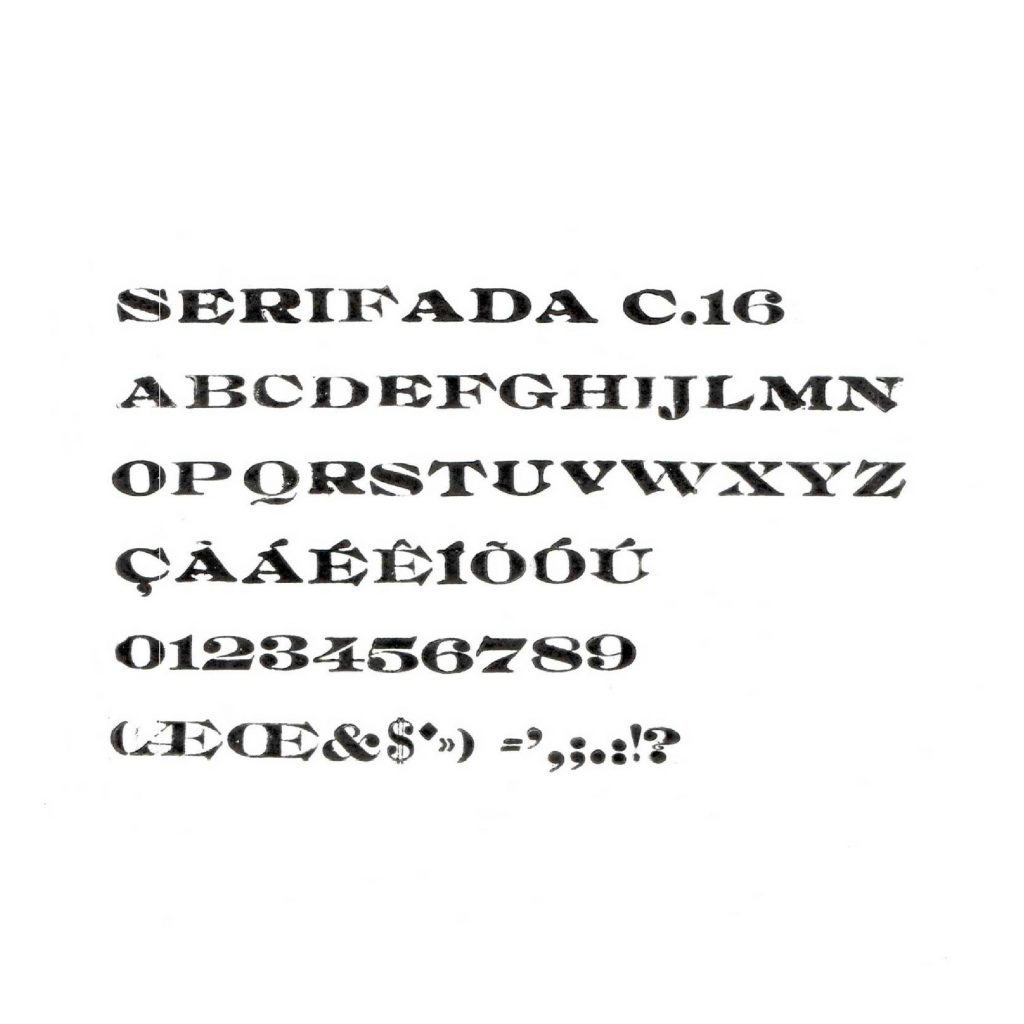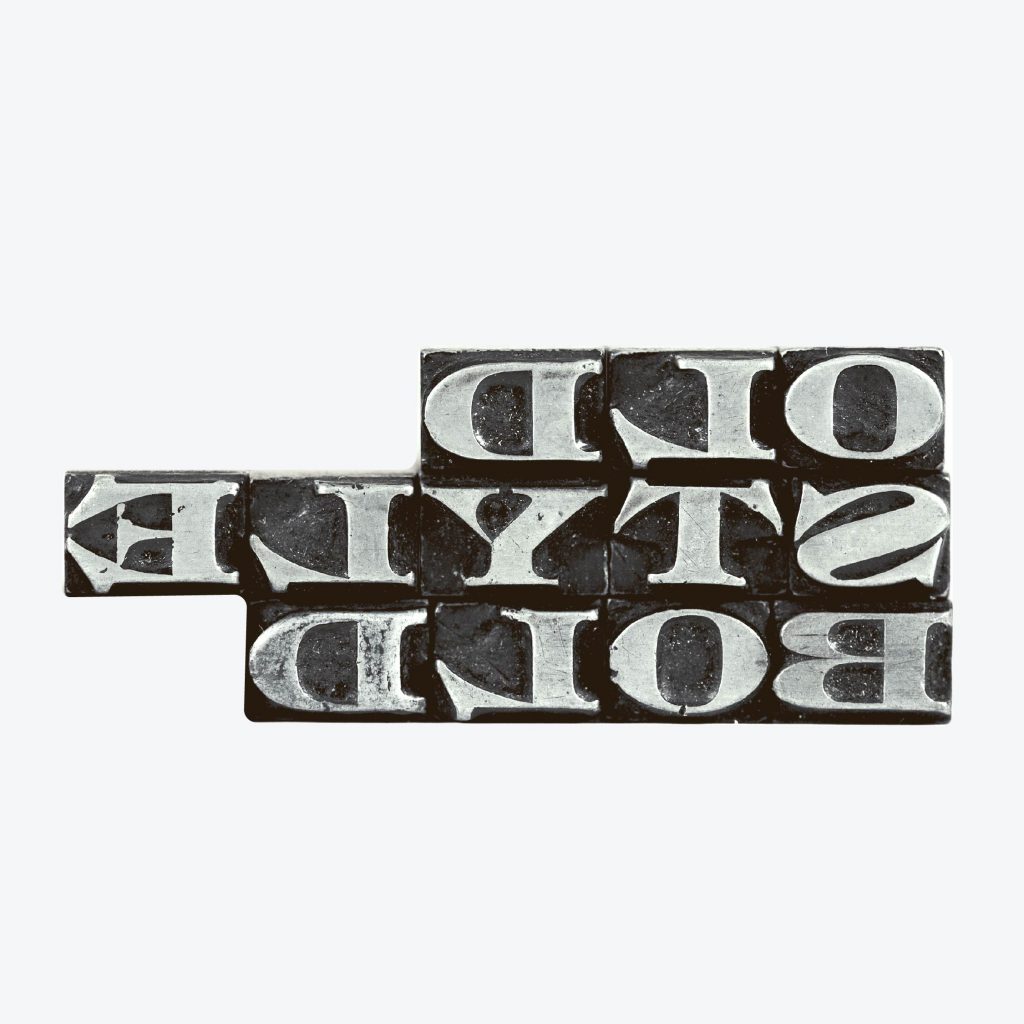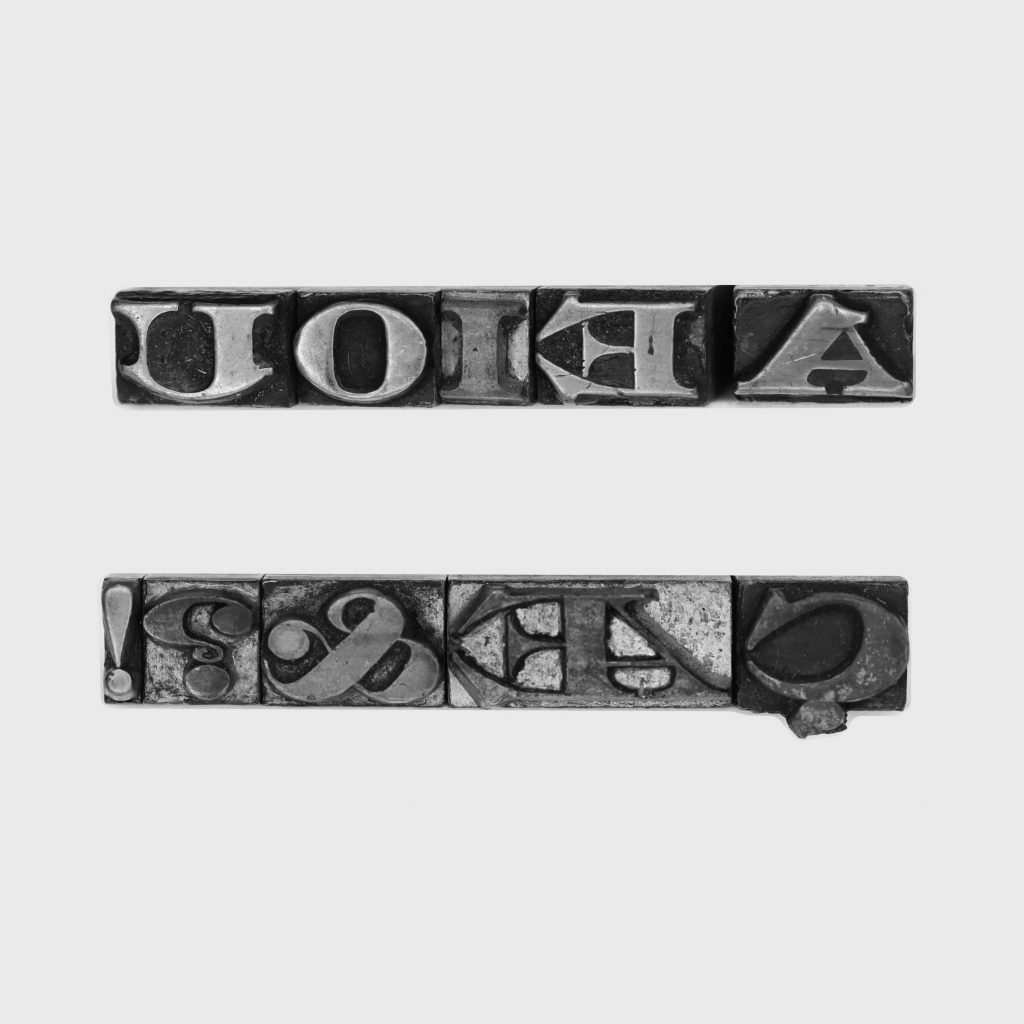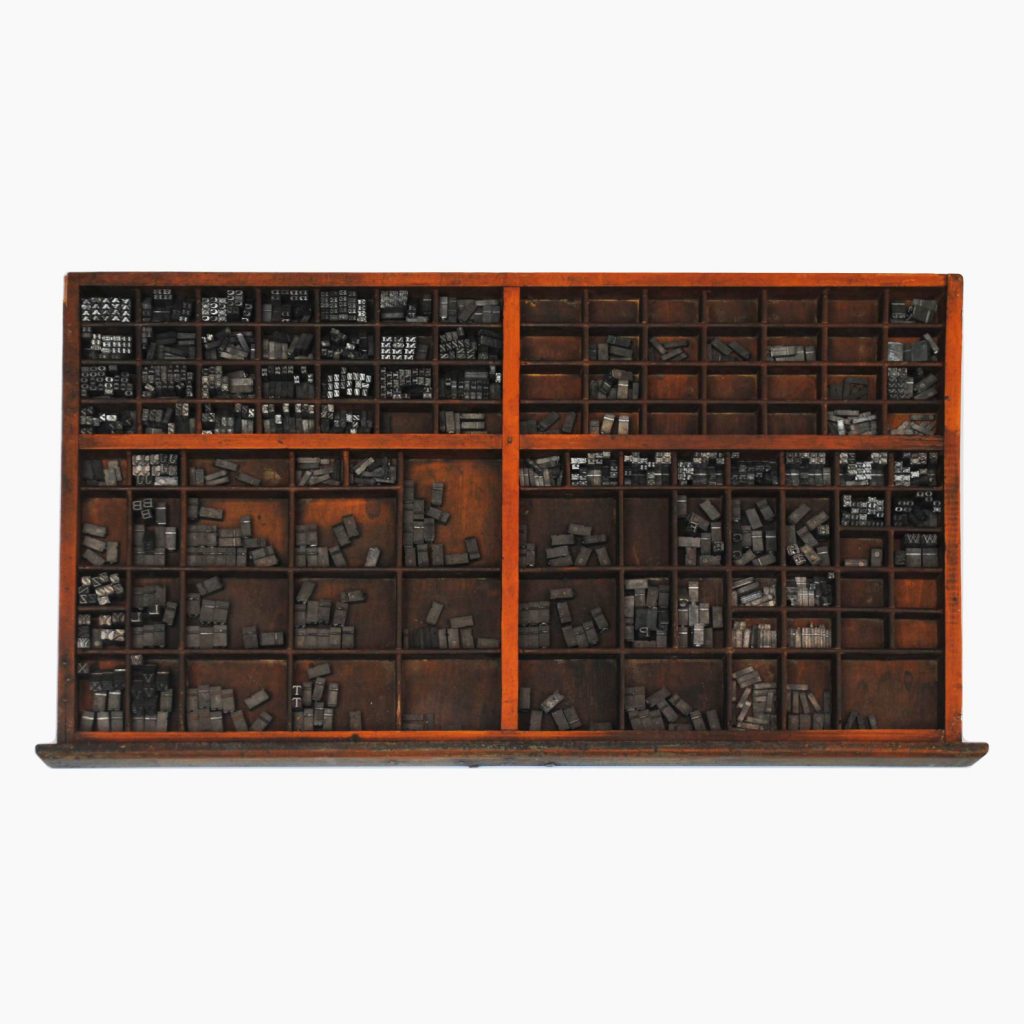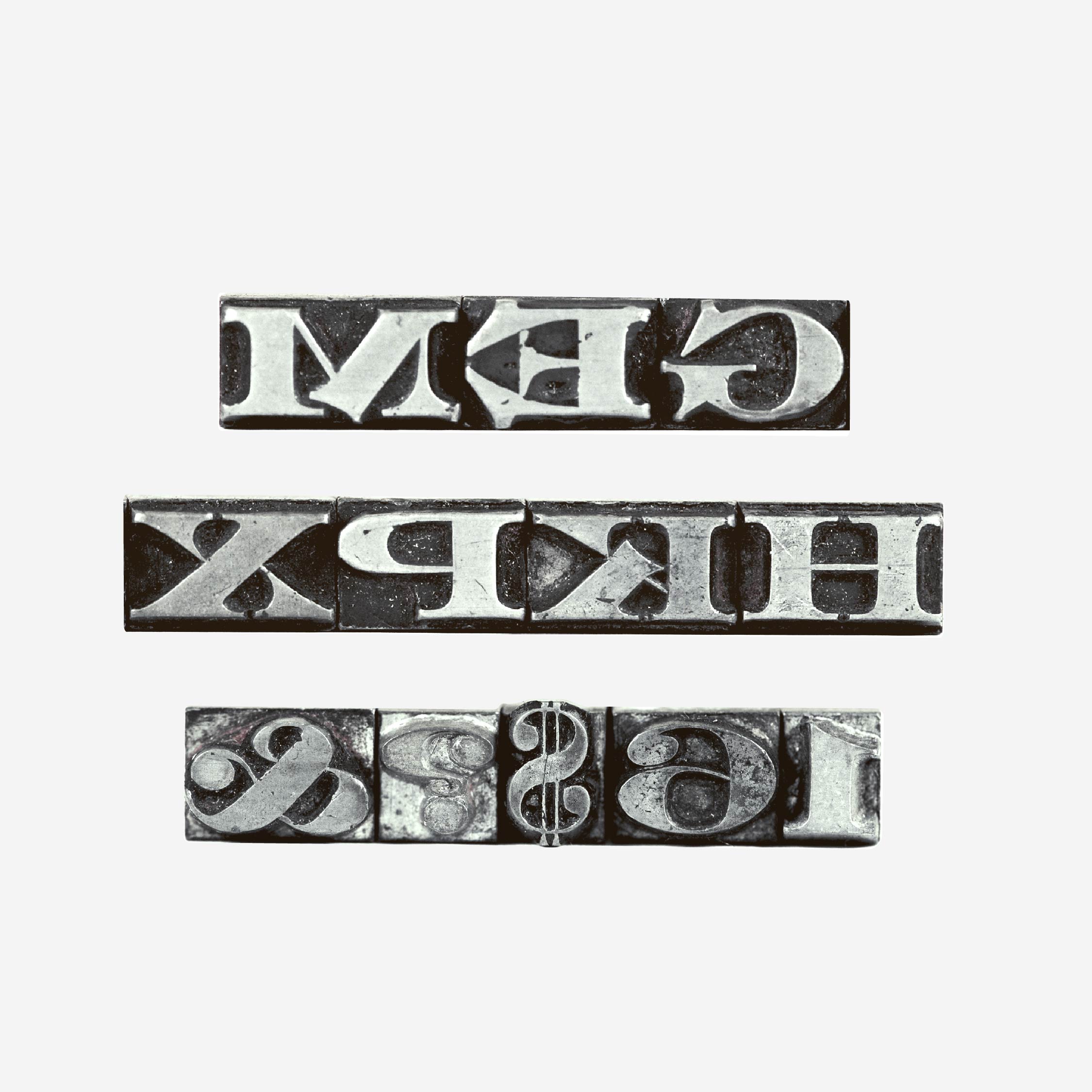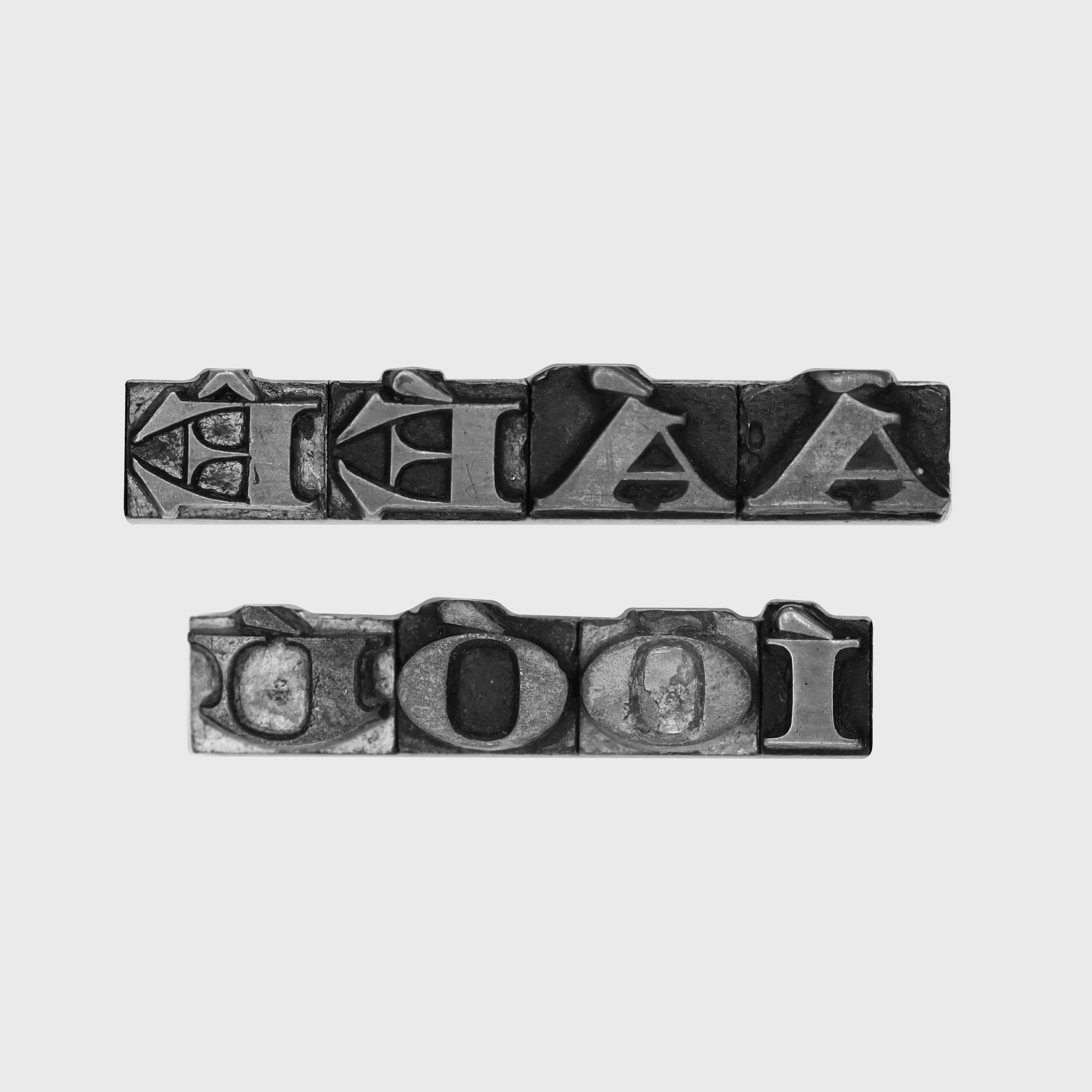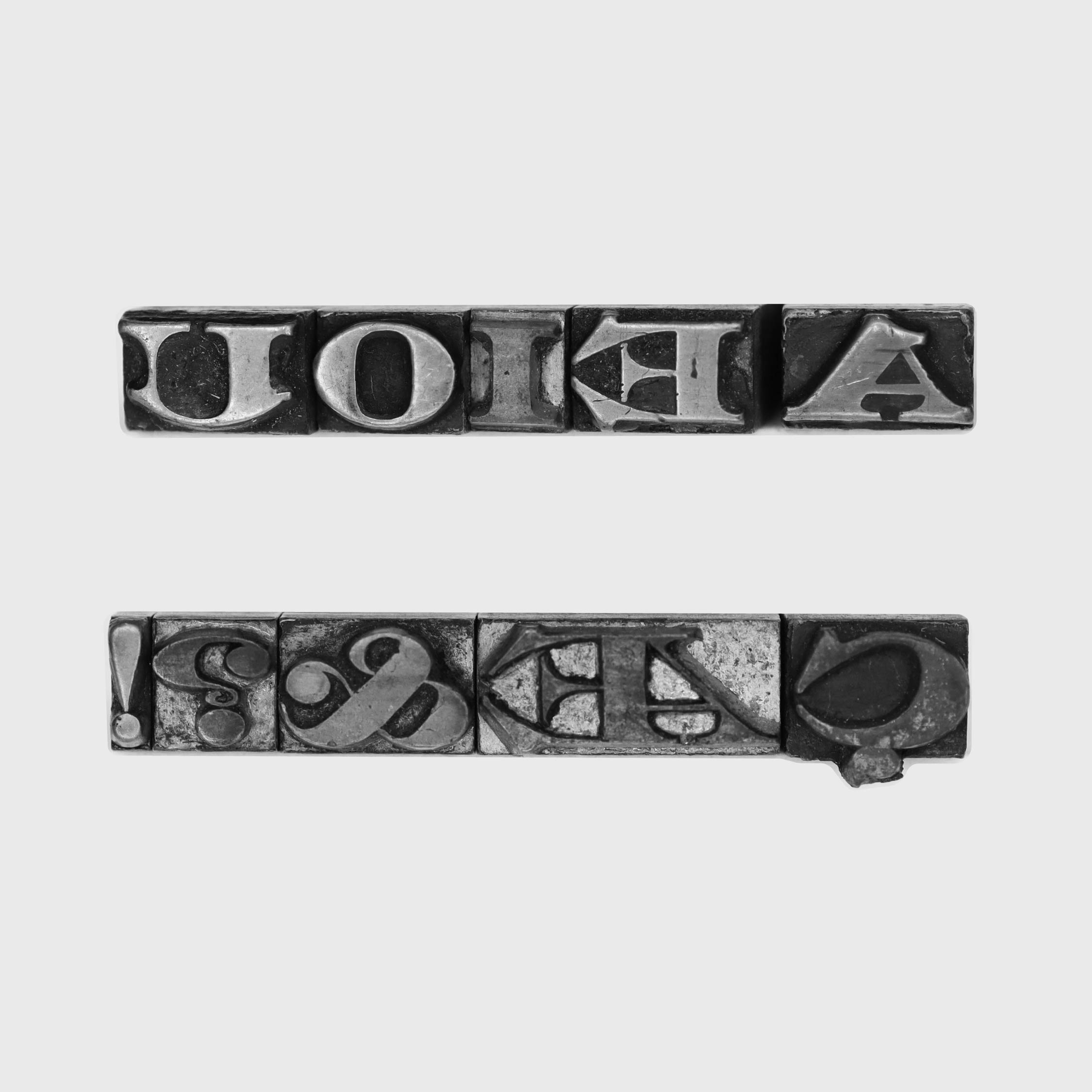
[Rinascimento Larghe Nere / Old Style Bold] 16 pt
Serifada
K, Q, R, U
Nebiolo [ca 1900]
EPS [s.d.]
ATF, 1896
Central Type Foundry and Boston Type Foundry, 1892
Marcas de uso recorrente; alguns tipos apresentam desgaste na face que pode comprometer a qualidade da impressão.
Faltam "À" e "Ì".
Foi identificado como visualmente correspondente à fonte Rinascimento Larghe Nere, no catálogo da Nebiolo (ca 1900, p. 32-33). Ao pesquisar pelo desenho original da fonte, ou o mais antigo, foi encontrada uma correspondência com a Old Style Bold (Thomas, F. F., 1896, p. 203). Trata-se de uma fonte criada pelo designer Gustave F. Schroeder em 1886 (Reichardt, 2011), comercializada por fundidoras americanas. A Old Style Bold foi encontrada em dois catálogos, um da American Type Founders (Thomas, 1896) e outro da Central Type Foundry and Boston Type Foundry (1892). Nos catalogos americanos os tipos são vendidos sob a a qualidade "copper alloy type", o que pode ser adição de ligas metalicas com cobre na composição. Embora não conhtenha marcas gravadas nos tipos, verificou-se que esta fonte consta no catálogo das Escolas Profissionais Salesianas, nos corpos 16 pt e 20 pt (s.d., p. 27), com numeração 220 e 221, com compatibilidade do caracter "R" no corpo 16 pt.